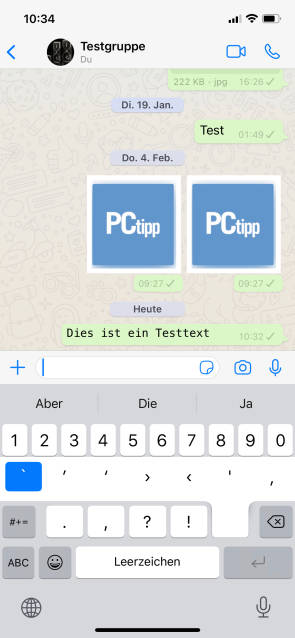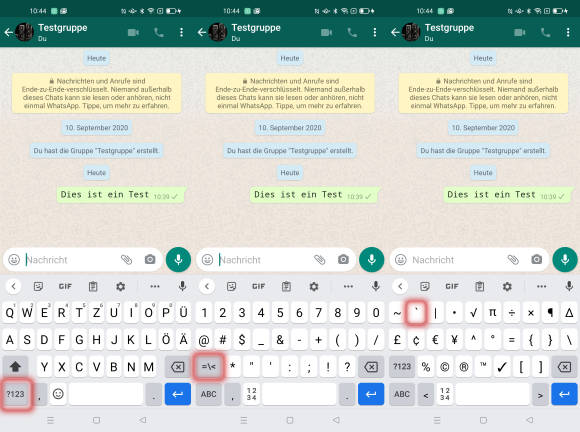
WhatsApp: So können Sie die Schriftart ändern
Bei WhatsApp kann man fett schreiben, kursiv oder auch durchgestrichen. Nicht viele Leute wissen aber, dass es eine versteckte Zweitschrift gibt.
WhatsApp beherbegt eine geheime Zweitschrift, wussten Sie das? Es ist eine Maschinenschrift. Es sieht dann also so aus, als wäre die Nachricht mit einer Oldschool-Schreibmaschine verfasst worden. Der Schlüssel zu dieser neuen Schrift ist das sogenannte Gravis-Zeichen. Wir zeigen, wies geht.
iOS
1. Öffnen Sie WhatsApp und einen beliebigen Chat.
2. Tippen Sie unten links auf die Taste ?123, danach auf #+=
3. Wählen Sie Apostroph, und halten Sie es gedrückt.
4. Das Gravis-Zeichen ist das äusserste Zeichen. Fügen Sie dies dreimal in die Nachricht ein (```).
5. Schreiben Sie Ihre Nachricht (ohne Abstand zwischen dem Zeichen und der Nachricht).
6. Fügen Sie das Gravis-Zeichen abermals ohne Abstand dreimal ein (```).
Android
1. Öffnen Sie WhatsApp und einen beliebigen Chat.
2. Tippen Sie unten links auf die Taste ?123, danach auf =\<
3. Wählen Sie das äusserste Apostroph, das Gravis-Zeichen und zwar dreimal (```).
4. Schreiben Sie Ihre Nachricht (ohne Abstand zwischen dem Zeichen und der Nachricht).
5. Fügen Sie das Gravis-Zeichen abermals ohne Abstand dreimal ein (```).